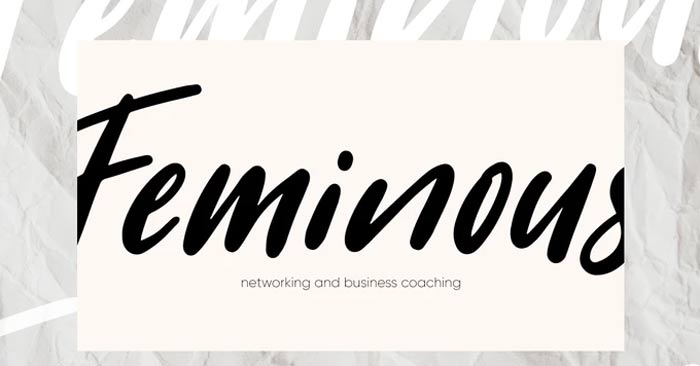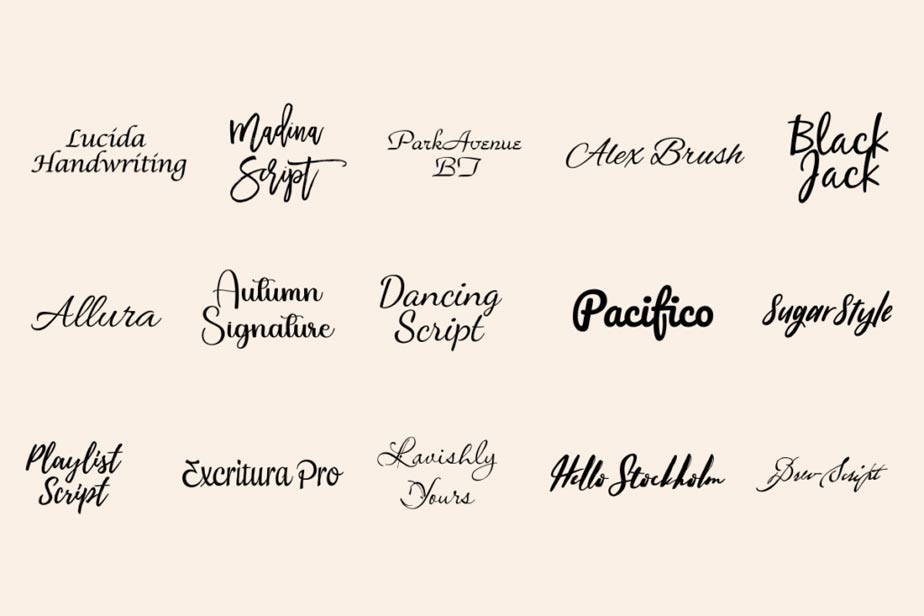
Những font chữ ký đẹp làm nổi bật thiết kế của bạn
Bạn muốn biến một văn bản bình thường thành thứ gì đó khó quên? Những font chữ ký tuyệt vời có thể biến đổi văn bản kỹ thuật số của bạn từ đơn giản thành ấn tượng chỉ trong vài giây. Cho dù bạn đang ký các tài liệu quan trọng hay tạo ra các thiết kế tuyệt đẹp, phông chữ phù hợp sẽ tạo nên sự khác biệt.
Hãy nghĩ về điều đó – các phông chữ tiêu chuẩn như Times New Roman hoàn thành tốt nhiệm vụ của nó, nhưng chúng thiếu nét cá nhân. Một phông chữ trông giống như chữ ký mang lại nét cá tính cho thiết kế của bạn thông qua các đường cong uyển chuyển, khuyết điểm tự nhiên và nét thanh lịch của nghệ thuật thư pháp hiện đại. Những chi tiết nhỏ này khiến chữ ký của bạn trở nên chân thực.
Phần tuyệt nhất là gì? Thêm nét cá nhân này dễ hơn bạn nghĩ. Không cần công cụ hay nhiều giờ luyện tập – chỉ cần chọn đúng font chữ ký và bạn đã sẵn sàng để tạo dấu ấn của mình. Dưới đây là những font chữ ký có thể nâng tầm các dự án sáng tạo của bạn từ cơ bản lên tuyệt vời.
Font chữ ký là gì?
Font chữ ký là kiểu chữ nắm bắt được bản chất của chữ ký viết tay. Chúng được đặc trưng bởi các đường cong thanh lịch, nhịp điệu tự nhiên và mang dấu ấn cá nhân. Những phông chữ này tạo nên sự cân bằng tinh tế giữa tính dễ đọc và biểu đạt nghệ thuật, khiến chúng trở nên lý tưởng để thêm tính xác thực và sự tinh tế vào nhiều dự án thiết kế khác nhau.
Các đặc điểm chính của font chữ chữ ký bao gồm:
• Nét chữ liên tục, mượt mà
• Độ dày nét chữ thay đổi
• Đường cong và vòng lặp hữu cơ
• Những điểm bất thường nhỏ để có vẻ ngoài tự nhiên hơn
• Các chữ cái kết nối thanh lịch
Sức hấp dẫn của font chữ ký nằm ở khả năng truyền tải cá tính và tạo ra sự kết nối cảm xúc với người xem. Chúng thêm nét nhân văn vào các thiết kế kỹ thuật số, thu hẹp khoảng cách giữa tính thẩm mỹ thủ công và tính thẩm mỹ do máy tính tạo ra.
Đối với tài liệu chuyên môn
• Lucida Handwriting – Lựa chọn hàng đầu cho các tài liệu kinh doanh và chữ ký chuyên nghiệp. Các nét chữ gọn gàng của nó vẫn dễ đọc đồng thời tạo thêm nét cá nhân.
• Madina Script – Phông chữ chữ ký tối giản mang đến sự chuyên nghiệp hiện đại cho mọi tài liệu. Hoàn hảo cho chữ ký số và danh thiếp.
• ParkAvenue BT – Tinh tế và thanh lịch, lý tưởng cho các giao tiếp cấp điều hành và tài liệu chính thức.
Đối với thương hiệu và tiếp thị
• Alex Brush – Giản dị nhưng thanh lịch, phông chữ này hoạt động tuyệt vời cho thương hiệu cá nhân và doanh nghiệp sáng tạo.
• Allura – Hiện đại và đa năng, tuyệt vời cho các tài liệu tiếp thị trên nhiều phương tiện khác nhau.
• Autumn Signature – Tự nhiên và chân thực, hoàn hảo cho các thương hiệu phong cách sống và doanh nghiệp chăm sóc sức khỏe.
Đối với nội dung kỹ thuật số
• Dancing Script – Thêm năng lượng và chuyển động vào các bài đăng trên phương tiện truyền thông xã hội và đồ họa kỹ thuật số.
• Pacifico – Thân thiện và dễ gần, tuyệt vời cho nội dung kỹ thuật số thông thường và các bài đăng trên mạng xã hội hấp dẫn.
• Playlist Script – Trẻ trung và năng động, lý tưởng cho nội dung giải trí và phương tiện truyền thông.
Đối với sự kiện sang trọng và đặc biệt
• ExcrituraPro – Sự thanh lịch cổ điển tỏa sáng trong các lời mời đám cưới và sự kiện trang trọng.
• Lavishly Yours – Tinh tế và phức tạp, hoàn hảo cho các thương hiệu xa xỉ và vật liệu cao cấp.
• Hello Stockholm – Sự sang trọng đương đại với phong cách thời trang tiên tiến.
Dành cho các dự án sáng tạo
• Blackjack – Đậm nét và khác biệt, tạo ấn tượng mạnh mẽ trên bao bì sản phẩm.
• Sugar Style – Vui tươi nhưng tinh tế, tuyệt vời cho các dự án sáng tạo cần nét cá nhân.
• Brew Script – Nét quyến rũ cổ điển kết hợp hoàn hảo với các thiết kế lấy cảm hứng từ phong cách hoài cổ.
Font trông giống chữ ký rất linh hoạt và có thể nâng cao nhiều dự án thiết kế khác nhau. Sau đây là một số ứng dụng phổ biến mà các phông chữ này phát huy tác dụng:
• Giấy chứng nhận và giải thưởng: Thêm uy tín và tính xác thực cho các tài liệu chính thức.
• Chữ ký số: Tạo nét cá nhân hóa trong email và hợp đồng kỹ thuật số.
• Vật liệu xây dựng thương hiệu: Nâng cao logo, danh thiếp và tài liệu tiếp thị.
• Văn phòng phẩm cưới: Mang lại sự thanh lịch cho lời mời, thiệp ghi tên và giấy cảm ơn.
• Bao bì sản phẩm: Thêm cảm giác cao cấp cho nhãn và thiết kế bao bì.
• Đồ họa truyền thông xã hội: Tạo trích dẫn và tiêu đề bắt mắt cho nội dung trực tuyến.
• Bìa sách: Thiết kế tiêu đề hấp dẫn cho tiểu thuyết và ấn phẩm.
Chìa khóa để sử dụng font chữ ký hiệu quả là tạo sự cân bằng giữa tác động và khả năng đọc. Sử dụng chúng làm phông chữ nhấn để làm nổi bật các yếu tố quan trọng trong khi vẫn duy trì khả năng đọc tổng thể trong thiết kế của bạn.